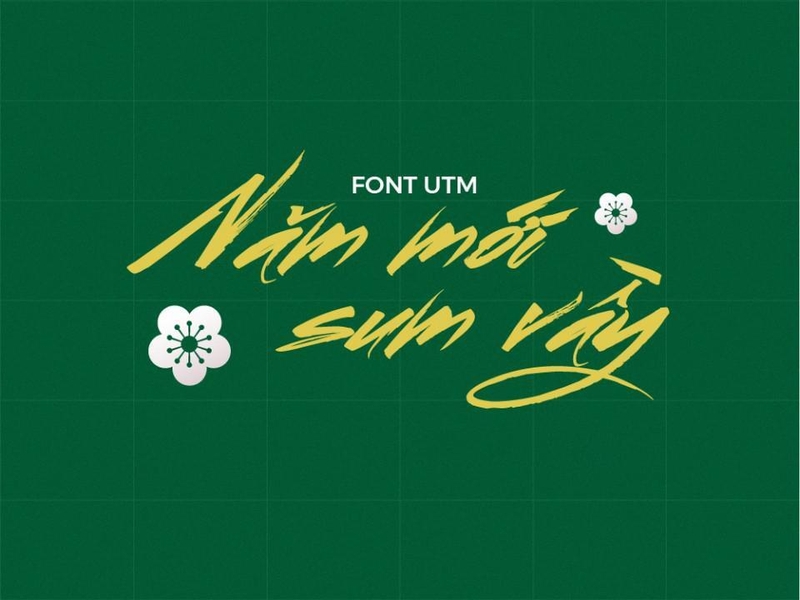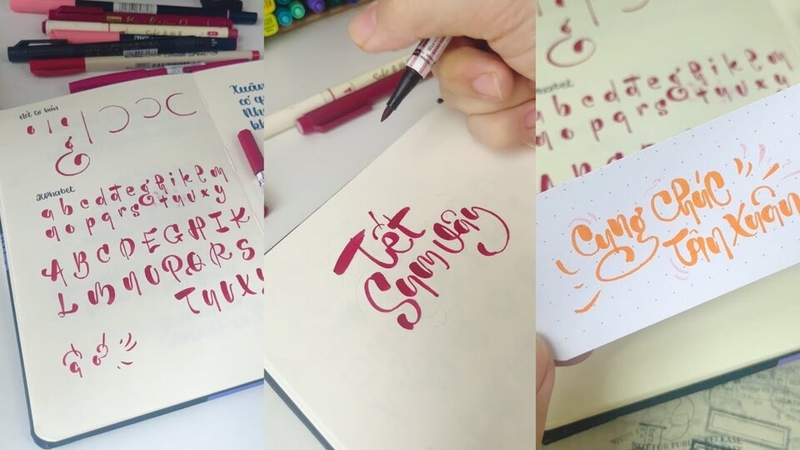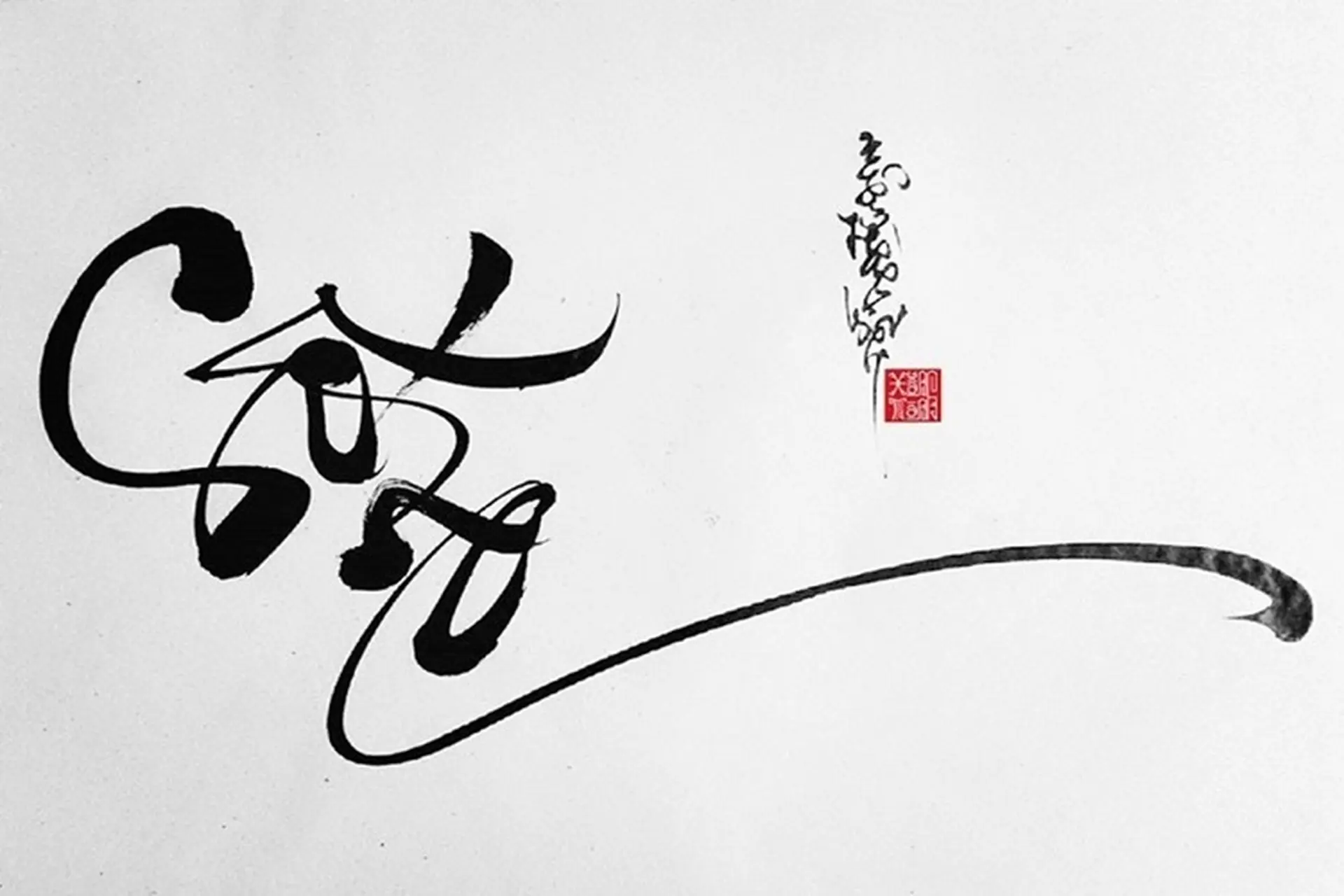
Font Thư Pháp Việt Hóa: Đánh thức nét đẹp truyền thống trong thiết kế hiện đại
Font chữ thư pháp đã trở thành một phần không thể thiếu trong việc thiết kế các ấn phẩm mang đậm dấu ấn truyền thống Việt Nam. Từ thiệp chúc Tết, tranh chữ đến các ấn phẩm quảng cáo mang đậm chất Á Đông. Nhu cầu sử dụng các font thư pháp Việt hóa trong thiết kế ngày càng tăng cao. Bài viết dưới đây sẽ tổng hợp những font thư pháp Việt hóa đẹp nhất, mang lại cảm hứng cho các nhà thiết kế và người yêu thích nghệ thuật chữ viết.
Font thư pháp Việt hóa là gì?
Font thư pháp Việt hóa là các kiểu chữ được thiết kế dựa trên nghệ thuật viết thư pháp truyền thống nhưng đã được tối ưu hóa cho tiếng Việt. Những font này không chỉ giữ nguyên vẻ đẹp uốn lượn, mềm mại của thư pháp mà còn hỗ trợ đầy đủ các dấu, chữ cái đặc trưng của tiếng Việt như â, ê, ơ, đ...
Thư pháp vốn là một loại hình nghệ thuật cổ truyền, xuất phát từ Trung Hoa và phát triển mạnh mẽ ở nhiều nước châu Á, trong đó có Việt Nam. Nhờ kỹ thuật Việt hóa font chữ, chúng ta có thể sử dụng chúng để tạo nên những tác phẩm đẹp mắt mà không gặp khó khăn về ngôn ngữ.
Tại sao font thư pháp Việt hóa được sử dụng nhiều?
Với vẻ đẹp mềm mại của font thư pháp vốn có, nay được Việt hoá để thuận tiện hơn trong việc sử dụng, font chữ này ngày càng được ưa chuộng.
Thể hiện nét đẹp truyền thống
Font thư pháp Việt hóa giúp người dùng thể hiện sự trang nhã, truyền thống và tinh tế trong các tác phẩm. Chúng thích hợp cho các thiết kế thiệp mời, ấn phẩm Tết, lời chúc phúc hoặc quảng cáo sản phẩm mang tính cổ truyền.
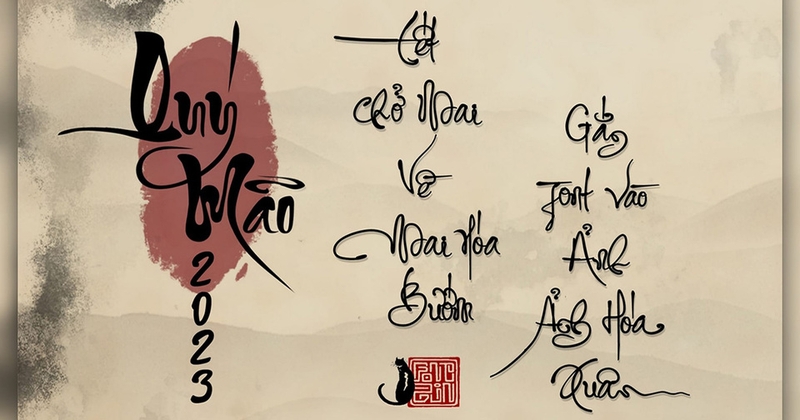
Đa dạng phong cách thiết kế
Có rất nhiều phong cách font thư pháp khác nhau, từ cổ điển, hiện đại đến các dạng cách tân. Điều này giúp các nhà thiết kế dễ dàng lựa chọn được kiểu chữ phù hợp với phong cách và mục tiêu sáng tạo của họ.
Đảm bảo tính thẩm mỹ
Nhờ quá trình Việt hóa, các font chữ thư pháp không chỉ đẹp mà còn hỗ trợ đầy đủ các ký tự tiếng Việt. Nhờ vậy các sản phẩm của bạn vẫn giữ được nét thẩm mỹ mà không phải lo lắng về vấn đề hiển thị sai hoặc thiếu dấu.
Thể hiện bản sắc văn hóa Việt
Sử dụng font thư pháp Việt hóa giúp thể hiện rõ nét bản sắc văn hóa truyền thống của Việt Nam, tạo sự gần gũi và thân thuộc với người xem. Điều này rất quan trọng trong thiết kế các sản phẩm hướng đến đối tượng người Việt.
Khắc phục hạn chế của font chữ Latin
Font thư pháp tiếng Anh thường không hỗ trợ tốt các dấu tiếng Việt, dẫn đến việc hiển thị bị lỗi hoặc không đẹp mắt. Font thư pháp Việt hóa đã giải quyết được vấn đề này, giúp hiển thị tiếng Việt một cách hoàn chỉnh và đẹp mắt.
Truyền tải thông điệp hiệu quả
Tùy thuộc vào phong cách thư pháp (thư pháp mạnh mẽ, mềm mại, uyển chuyển…), font chữ sẽ giúp truyền tải được thông điệp, cảm xúc khác nhau đến người xem. Ví dụ, một loại font thư pháp mạnh mẽ sẽ phù hợp cho các mẫu thiết kế mang tính chất quyền lực. Trong khi đó, một loại font thư pháp mềm mại lại thích hợp cho các mẫu thiết kế nhẹ nhàng, nữ tính.
Top những font thư pháp Việt hóa đẹp nhất
Dưới đây là gợi ý top 6 mẫu font thư pháp Việt hoá đẹp và sáng tạo nhất mà bạn có thể tham khảo.
Font UTM thư pháp Thiên Ân
Font UTM thư pháp Thiên Ân là một trong những font thư pháp Việt hóa nổi bật, mang đậm nét truyền thống nhưng không kém phần hiện đại. Với các đường nét mềm mại, uyển chuyển, font này tạo ra cảm giác thanh thoát, nhẹ nhàng, phù hợp cho các thiết kế liên quan đến văn hóa, nghệ thuật và lễ hội.
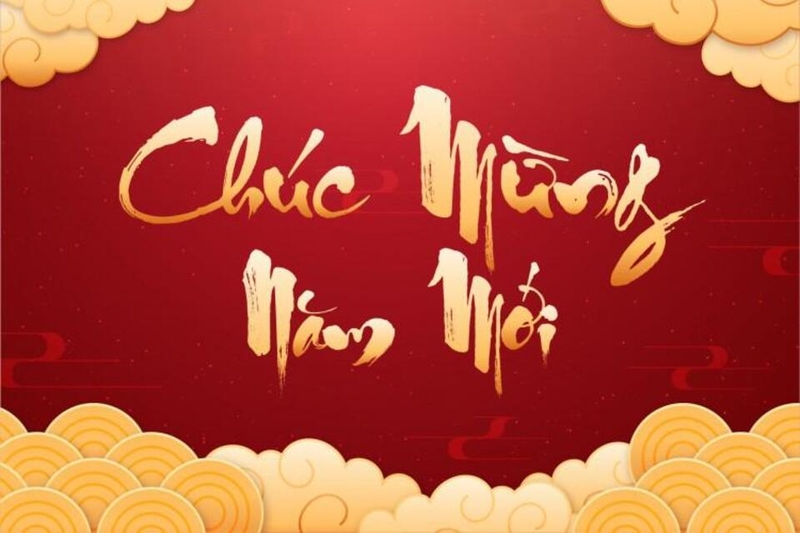
Font thư pháp Xuân
Font thư pháp Xuân mang lại sự tươi mới, trẻ trung, thích hợp cho các thiết kế chào đón mùa xuân, đặc biệt là các ấn phẩm Tết. Các nét chữ uyển chuyển và mạnh mẽ của font này giúp tăng thêm tính sinh động cho tác phẩm.
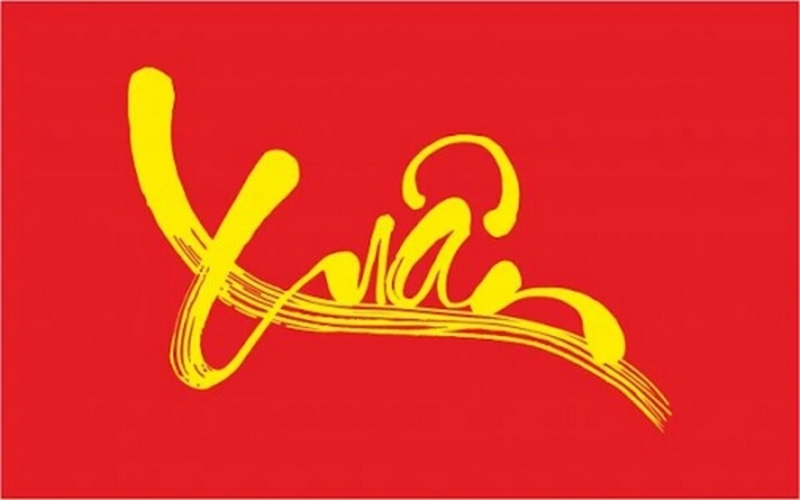
Font UVN mực chấm
Font thư pháp Việt hóa UVN mực chấm là một kiểu chữ độc đáo, mô phỏng các nét bút lông chấm phá, mang đậm phong cách thư pháp truyền thống. Với các nét chữ đậm, nhấn nhá như những giọt mực tự nhiên, font này tạo ra cảm giác mộc mạc và chân thật, phù hợp cho các thiết kế mang tính cổ điển, văn hóa dân tộc.
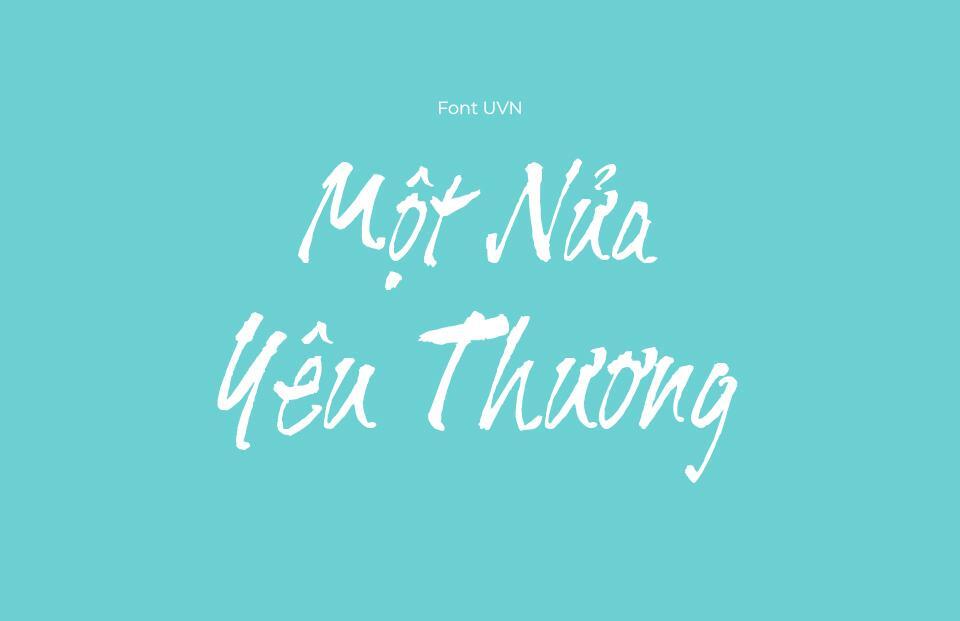
Đây là một font chữ được thiết kế đặc biệt, mô phỏng kiểu chữ viết tay bằng mực chấm (hay còn gọi là chấm bi). Điểm nổi bật của font này nằm ở sự mềm mại, tự nhiên, gần gũi, mang lại cảm giác thân thiện và dễ gần. Nó thường được sử dụng để tạo nên vẻ đẹp vintage, hoài cổ hoặc tạo điểm nhấn trẻ trung, năng động tùy thuộc vào ngữ cảnh.
Font MTD Addictype
Font Việt hóa MTD Addictype là một font chữ thư pháp hiện đại, mang đến sự kết hợp hài hòa giữa nét thanh thoát và sự phóng khoáng trong từng nét chữ. Được Việt hóa hoàn chỉnh, font này hỗ trợ đầy đủ các ký tự tiếng Việt, giúp người dùng dễ dàng áp dụng trong các thiết kế sáng tạo.
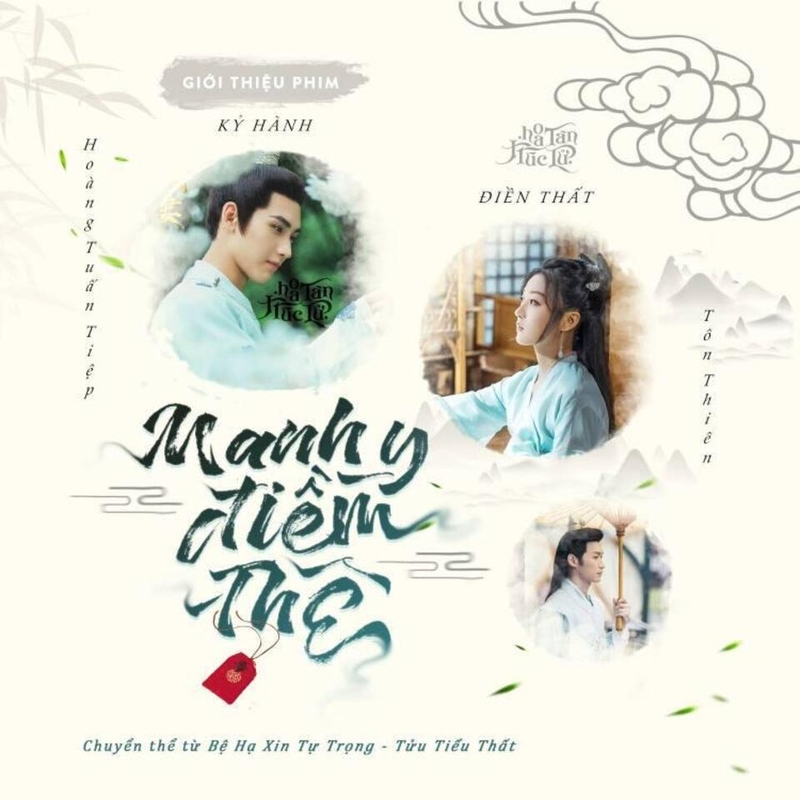
Font LNTH Adelia
Font Việt hóa LNTH Adelia là một kiểu chữ thư pháp mềm mại và tinh tế, được Việt hóa để hỗ trợ đầy đủ các ký tự tiếng Việt. Font này nổi bật với những nét uốn lượn uyển chuyển, mang đậm hơi hướng lãng mạn và nghệ thuật.
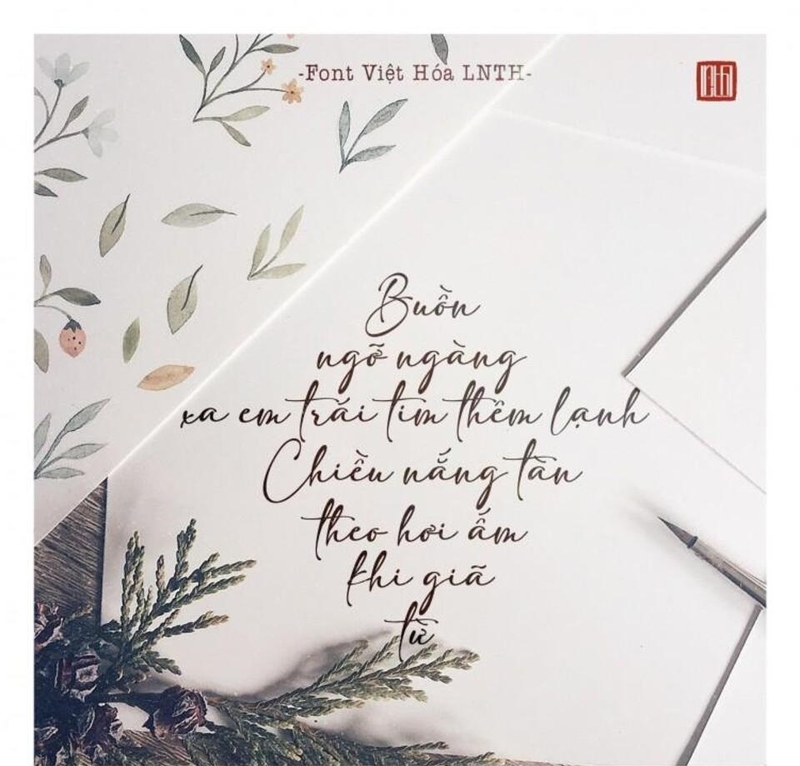
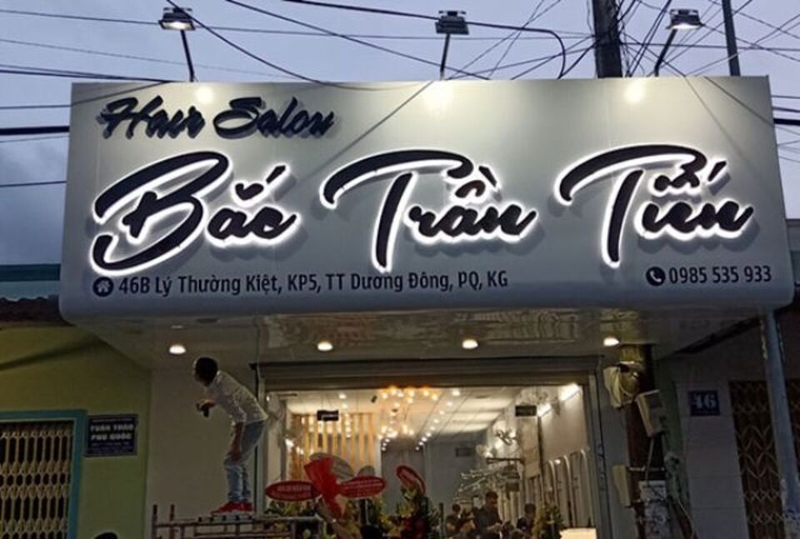
Tạm kết
Font thư pháp Việt hóa không chỉ là công cụ hỗ trợ thiết kế mà còn là phương tiện để truyền tải nét đẹp văn hóa truyền thống. Hy vọng với tổng hợp những font thư pháp Việt hóa đẹp trên bạn sẽ có thêm nhiều lựa chọn để sáng tạo những tác phẩm ấn tượng và độc đáo.